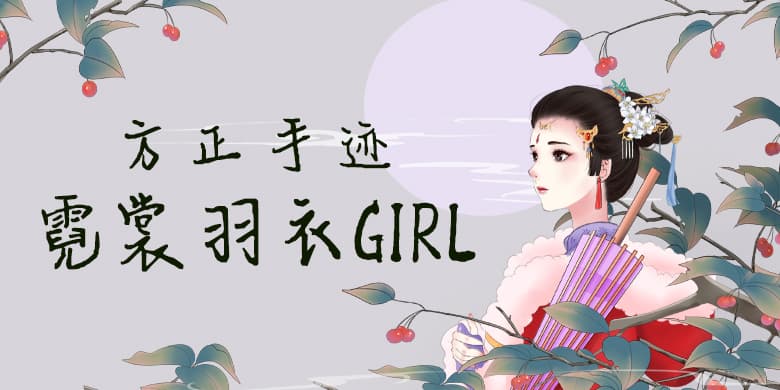
品牌:方正手迹设计师:李飒发行时间:2020字库编码:大陆简体(GB2312-80)分类:常规书写·硬笔字体属性:精品字
该字用笔飘逸灵动,结字秀美洒脱,霓裳羽衣girl,字如其名。结字与用笔都有传统书法的影子,作者有一定的传统书法的功力。适用于现代诗歌、短文的排版以及文化、商业类品牌的广告语设计。